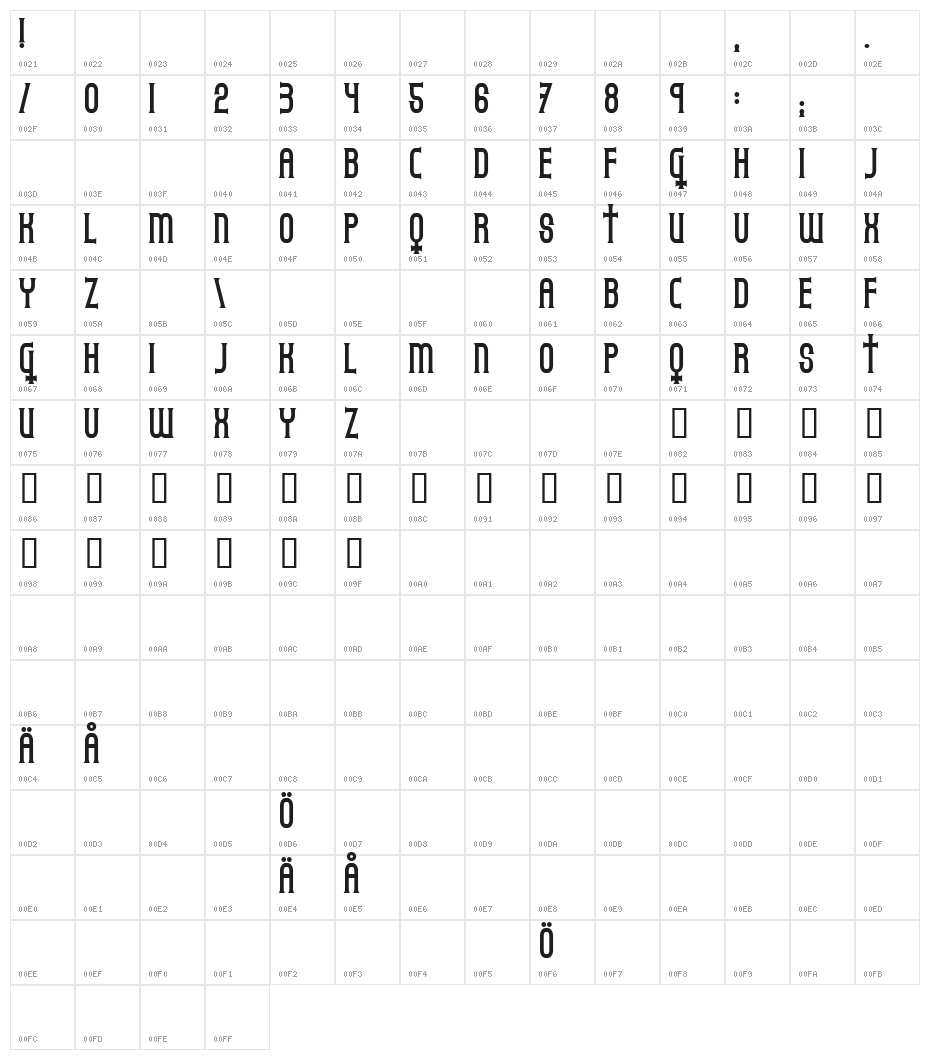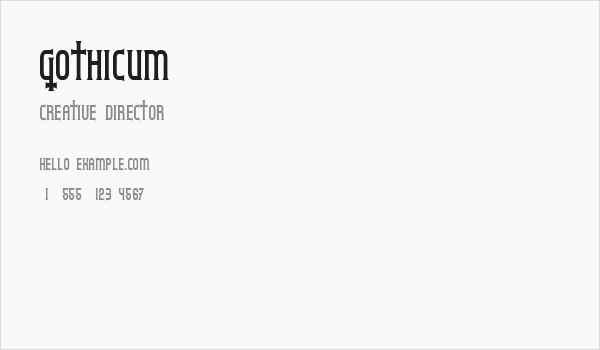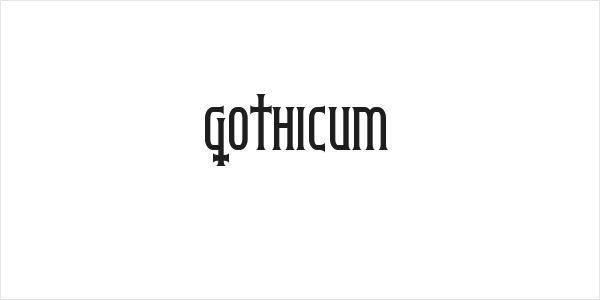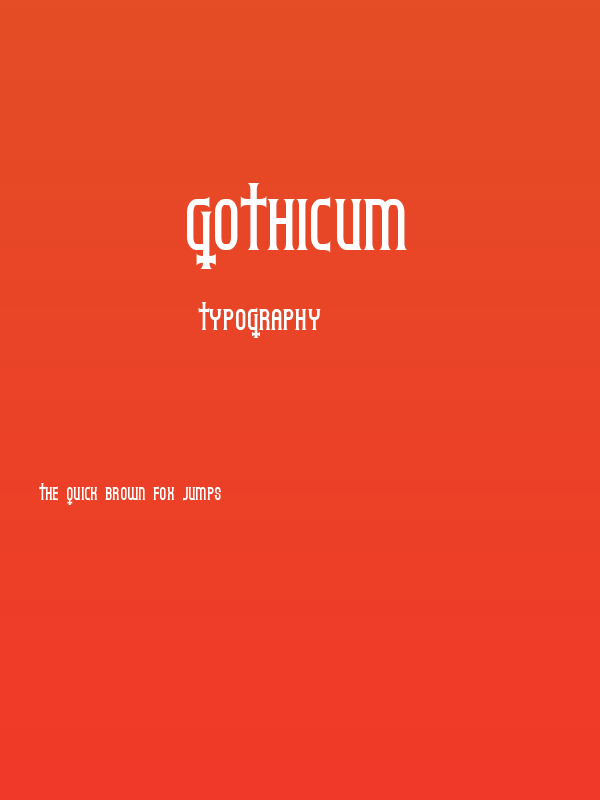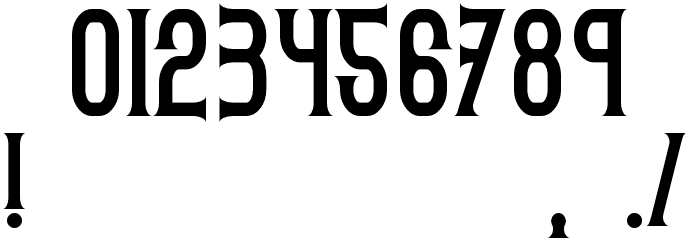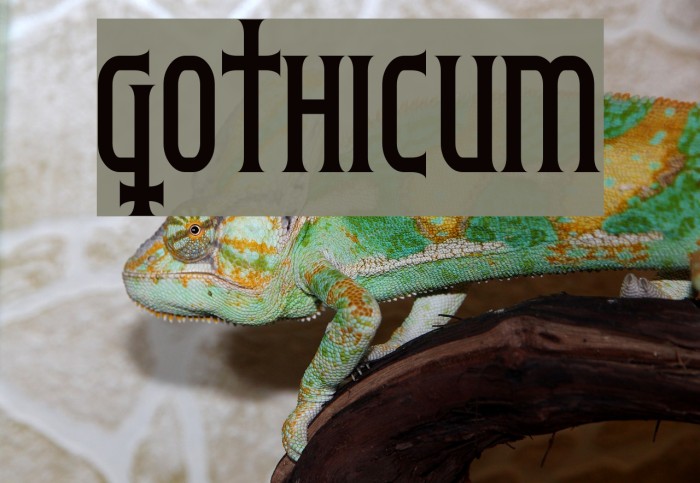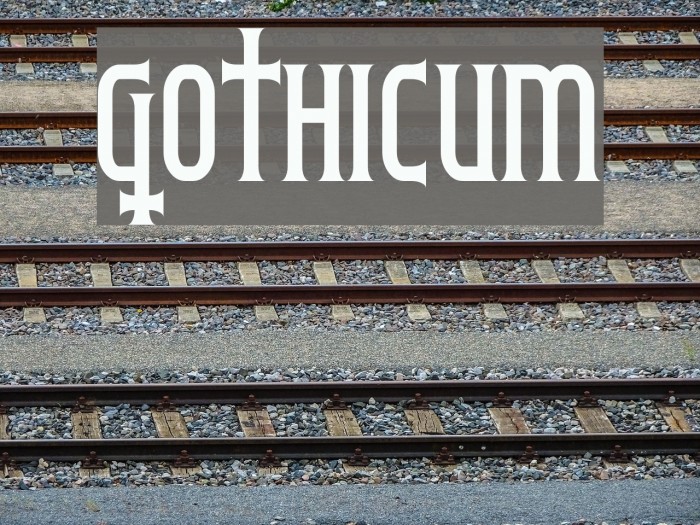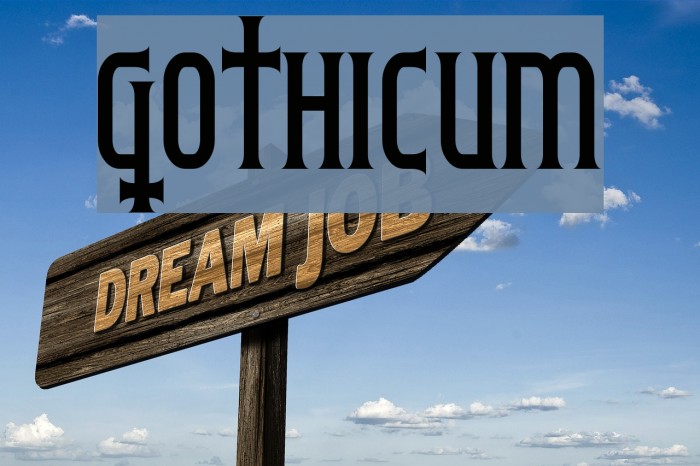
Gothicum Font
| Progetti proposti | Ideal for projects requiring a medieval or historical theme, such as book covers, posters, or branding for events like Renaissance fairs. |